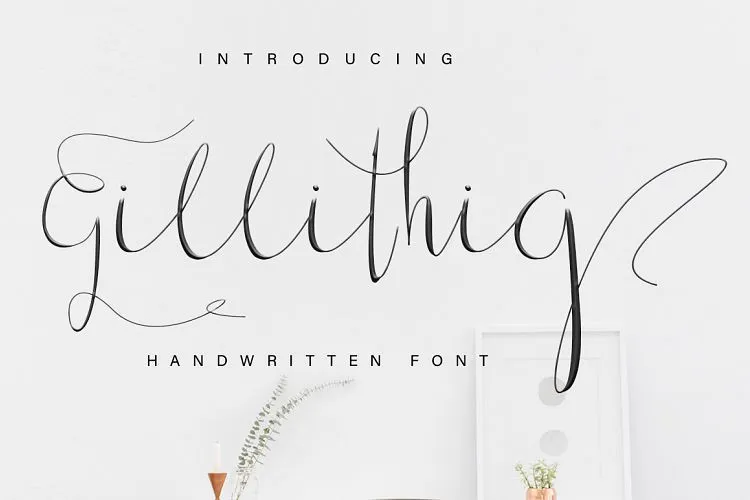
Gillithig Script Font
Bem-vindo à categoria de fonts Script na nossa loja virtual! Aqui está uma fonte chamada Gillithig Font que traz consigo um toque de romantismo e elegância para seus projetos digitais. Esse é o resultado perfeito da mão humana, cuidadosamente escrita em letras corridas e orgânicas, com um tom casual e suave que se torna uma peça única e incrível. O designer M.0Type criou Gillithig Font pensando no momento especial ou na tarefa especial que você está realizando agora. Suavemente delicado para mulheres e também elegante, esta font é a escolha perfeita para destacar qualquer design. Ficará perfeito em aplicativos de marca, convites de casamento, revistas, pratos, cartões de negócios, frases inspiradoras, cartazes e muito mais. Seja sua próxima criação digitálida, Gillithig Font se destaca com seu estilo elegante e feminino, criando um toque especial que faz a diferença em qualquer projeto!